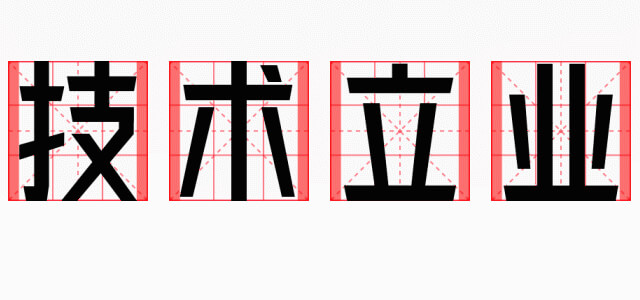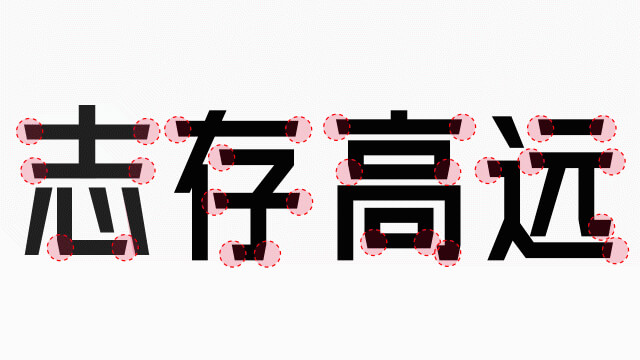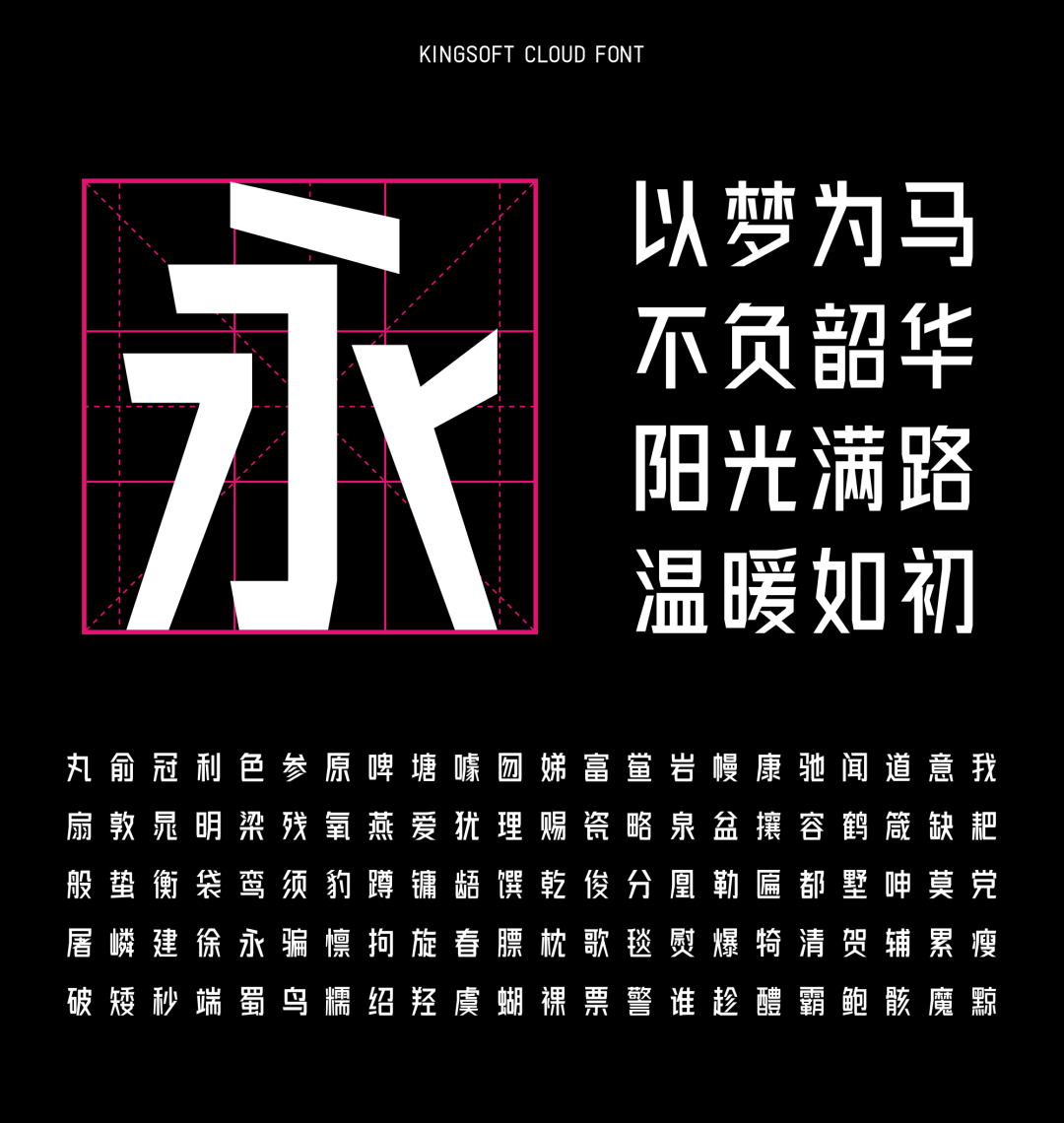
33年前,金山软件因“字”而生,33年后,金山云发布首款原创字体库,金山云UED设计团队,秉持着金山人“技术立业”的精神,历时四年,逐点逐字,匠心设计。
“金山云技术体”是一款无衬线体,提供一种标准版字重,文字参照GB2312简体中文编码字符标准。包含国标一级、二级字库汉字6763个,外文及数字符号804个,总字符数7567个。
设计理念:字体在整体造型设计上,风格偏向年轻、硬朗、具有活力。
设计师:金山云用户体验部的视觉设计同学们,历时4年完成字库,参与到字体制作的设计师(宋辉、李业鹏、刘雨凡、解磊、郭嘉琦、张立明、冯芷欣、王鹏飞、毛燕妮、闫佳妮、王思雨、张婧雨、刘淼)。
重新定义1:0.84的字宽比例,设计了整体、左右、上下等搭配方法。让笔划多的字与少的字,放在一起看尽量协调,减少视觉疏密感。
笔划:为了打破常规黑体的生硬感,我们选择了最复杂的设计方案,字体的笔划设计根据整字权重划分粗细进行搭配。
修饰:在笔划的衔接和末端处,使用了12度的倾斜设计。